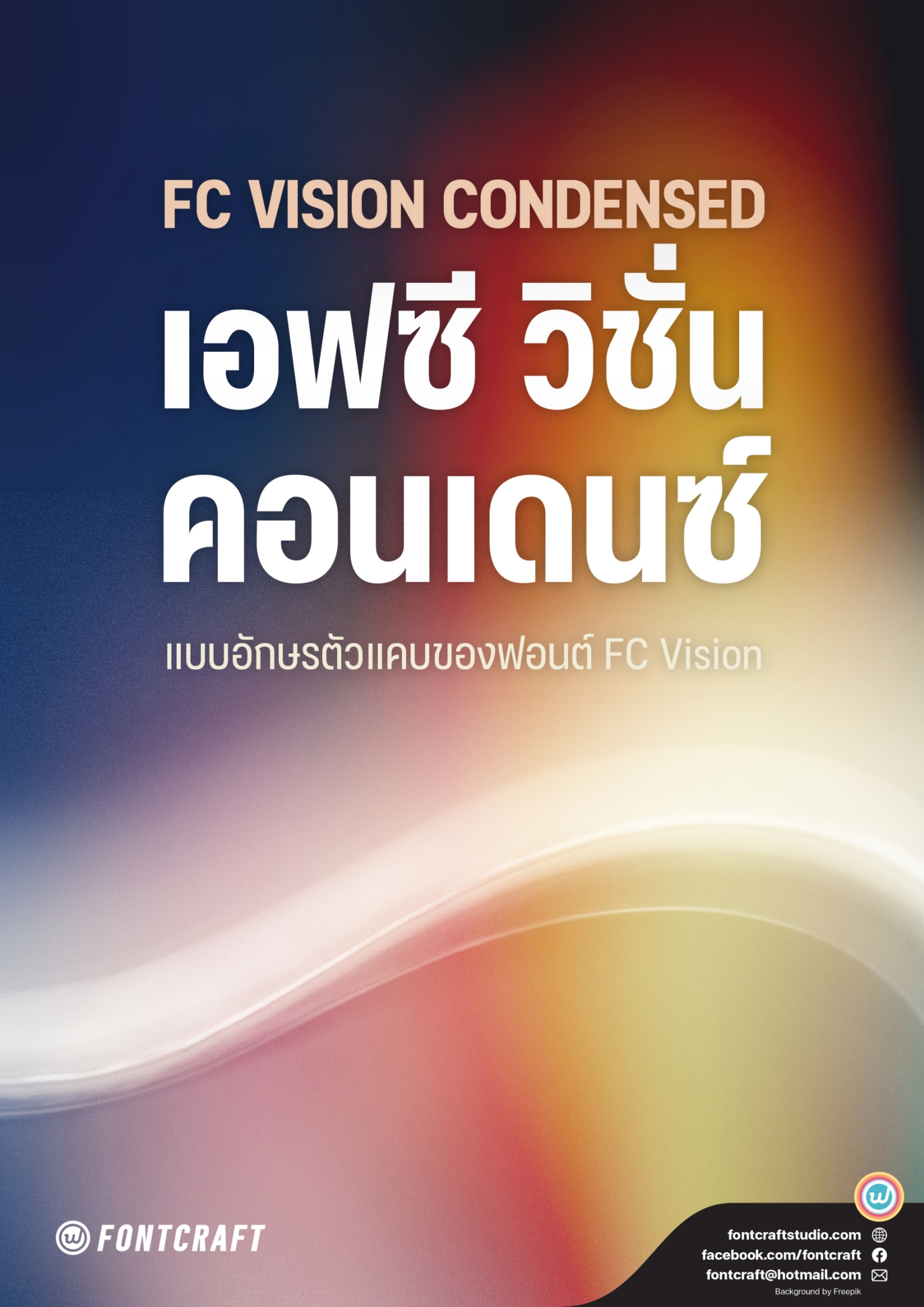
เอฟซี วิชั่น คอนเดนซ์ (FC Vision Condensed)
ฟอนต์เอฟซี วิชั่น คอนเดนซ์ (FC Vision Condensed)
เพิ่มความกว้างระหว่างกลาง เพื่อครอบคลุมทุกการใช้งานครับ
ฟอนต์เอฟซี วิชั่น คอนเดนซ์ (FC Vision Condensed)
แบบอักษรตัวแคบของฟอนต์เอฟซี วิชั่น
รูปแบบทางเลือกตัวแคบ (Condensed) ซึ่งอยู่ระหว่างตัวบีบ (Compressed) และตัวความกว้างปกติ (Normal) ใช้พื้นที่น้อยลง 15% มีให้เลือกใช้ครอบคลุมในทุกระดับน้ำหนัก และปรับได้โดยละเอียดผ่าน Variable Font